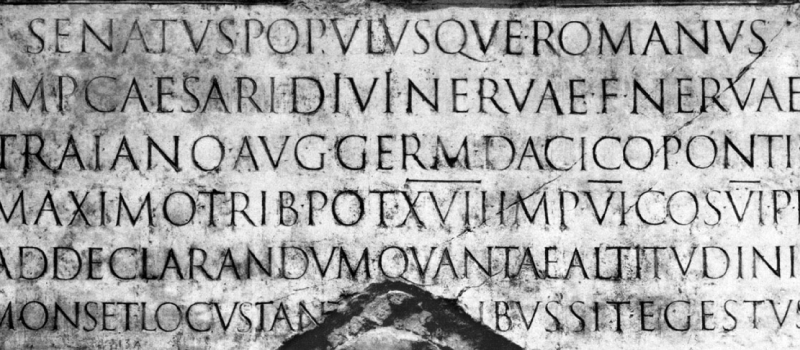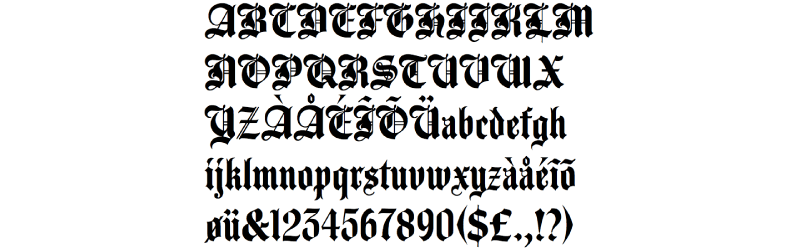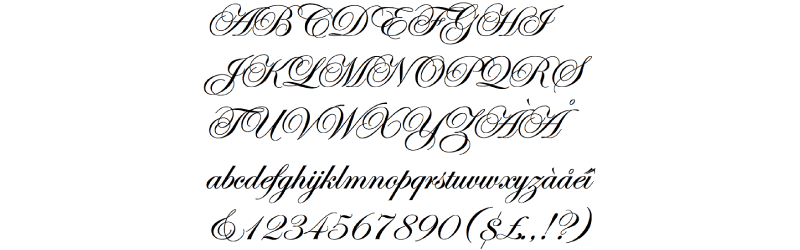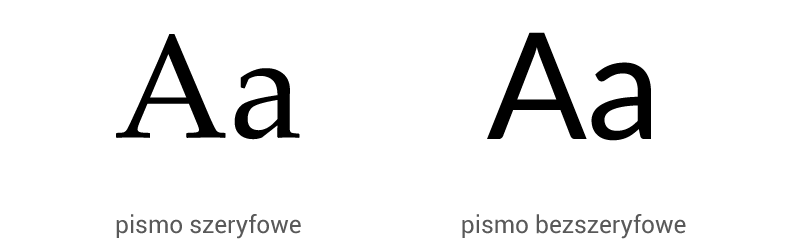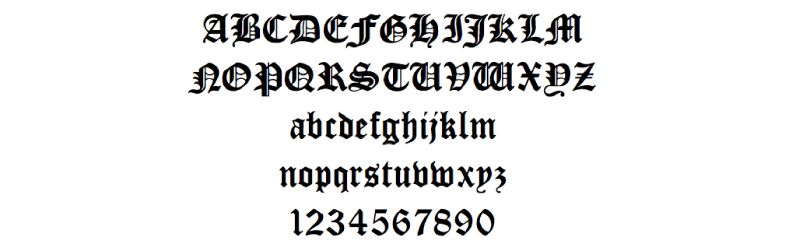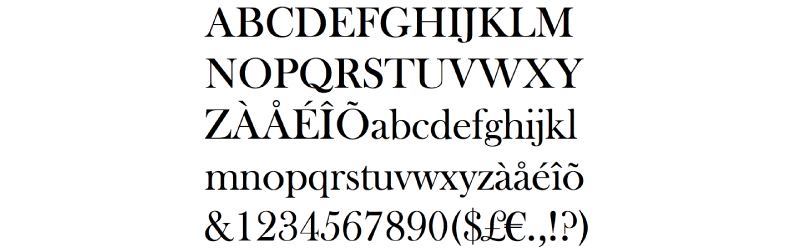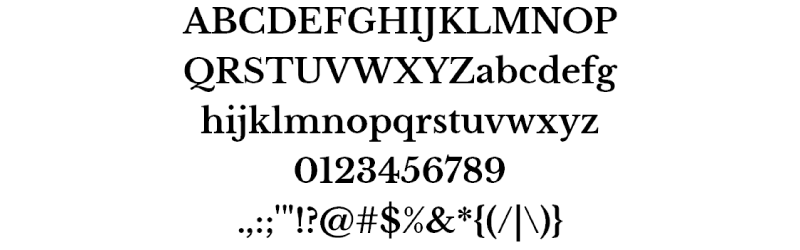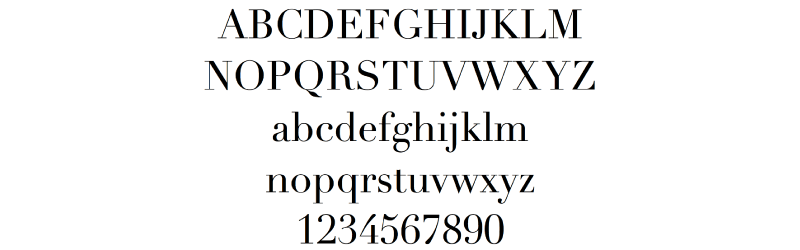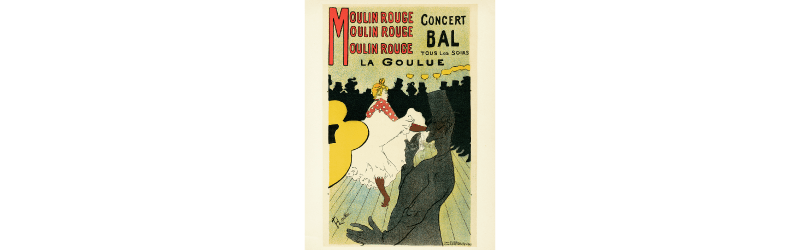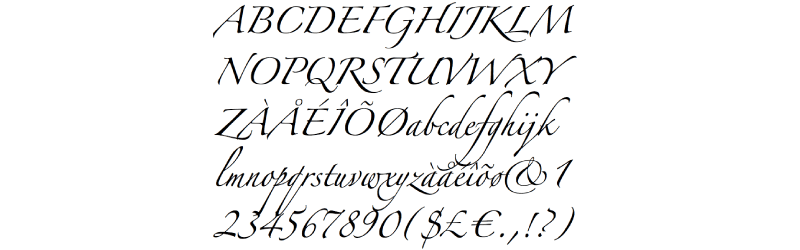
Z typografią stykamy się niemal wszędzie. Dobór kroju pisma może znacznie poprawić lub pogorszyć wygląd finalnego projektu, bądź podkreślić wartość merytoryczną przekazywanych słów. Coraz większą uwagę przykładamy do tego z jakiego kroju pisma korzystamy w różnych typach treści. Jednak skład tekstu nie sprowadza się tylko do wybrania odpowiedniego fontu - warto wiedzieć nieco więcej na ten temat, by tekst przez nas przygotowywany był łatwy do odczytania i zgadzał się z jego przeznaczeniem.
Skąd pochodzi nasz alfabet?
Na początek przyjrzyjmy się budowie liter. Alfabet rzymski, którym się posługujemy, wywodzi się ze starożytnego Rzymu, a pierwotnie służył wyłącznie do zapisu łaciny. Litery te mają charakterystyczne szerokie kreski na zakończeniu każdej linii tworzącej literę (szeryfy), a powstały one w wyniku technik, jakich wtedy używano - litery wykuwane były zapisywane za pomocą patyczka o ściętej pod skosem końcówce, lub wykuwane dłutem w kamieniu- oba narzędzia pozostawiały ślad w postaci takiej kreski właśnie. Rzymianie ogromną uwagę przykładali do harmonii optycznej w zapisie liter, stąd stosowanie węższych i szerszych linii w ich budowie, a także matematycznie obliczone wielkości zastosowanych liter. Dotychczas pismo zapisywane było wyłącznie za pomocą wielkich liter. Tablica z Kolumny Trajana na Forum Romanum jest uznawana za wzorzec litery alfabetu rzymskiego.
Podstawowe pojęcia z zakresu typografii to:
- majuskuła - wielka litera
- minuskuła - mała litera
- światło międzyliterowe - obszar niezadrukowany pomiędzy jednym, a drugim znakiem
- światło międzyliterowe - obszar niezadrukowany wewnątrz znaku
- kerning - odległość pomiędzy znakami
- ligartura - łączenia dwóch znaków
Podstawowymi rodzajami na jakie możemy podzielić kroje pisma są:
- pismo szeryfowe (serif) - czyli takie, w których występują szeryfy
- pismo bezszeryfowe (sans serif) - gdzie szeryfy nie występują
Nie istnieje jeden, ogólnie przyjęty system klasyfikacji poszczególnych krojów, jednak najbardziej popularnym jest system wprowadzony przez firmę Adobe i to na nim się skupimy.
Pismo gotyckie (Blackletter)
Ten typ krojów swą angielską nazwę zawdzięcza wrażeniu, jakie daje zadrukowana w ten sposób strona- wydaje się ona ciemna, a pismo ciężkie. Litery są zbudowane z linii o różnej szerokości.
Antykwy renesansowe (Old Face)
Ten typ to kroje lekkie, o zróżnicowanych szerokościach linii i subtelnych łukach.
Antykwy barokowe (Transitional)
Stanowią przejście pomiędzy antykwami renesansowymi a klasycystycznymi, dlatego zachowują niektóre cechy z obu typów. W odróżnieniu do antykw renesansowych posiadają większy kontrast w światłach znaków, a wydłużenia minuskuł zazwyczaj nie wystają ponad majuskuły.
Antykwy klasycystyczne (Modern, Didone)
Ten typ krojów pisma pojawił się wraz z techniką miedziorytu, który pozwalał na zastosowanie mocno kontrastowych grubości linii tworzących znak.
Antykwy linearne bezszeryfowe (Gothic, Sans Serif, Grotesque)
Wraz z rozkwitem przemysłu i reklamy zaczęto używać krojów bezszeryfowych, łatwiej czytelnych z odległości, świetnie nadających się na różnego rodzaju afisze i reklamy.
Pisanki
Wszystkie czcionki którymi obecnie się posługujemy mają swoje korzenie w którymś z powyższych typów. Istnieją jednak również tzw. pisanki - kroje, które imitują odręczny charakter pisma, w mniej lub bardziej ozdobny sposób. Z reguły dzielą się one na:
Pisanki kaligraficzne
pochodzące od kaligrafii, sprawiające wrażenie pisania wyprofilowanym pędzlem
Pisanki niedbałe
imitujące pismo wykonane zwykłym pisakiem bądź pędzlem
Pisanki gotyckie
powstałe w oparciu o średniowieczne manuskrypty, rzadko używane ze względu na utrudnioną czytelność
Pisanki angielskie
pochodzące od oficjalnego pisma odręcznego w XVIII w. Przez swoją elegancką formę często wykorzystywane w różnego rodzaju zaproszeniach, nagłówkach- wszędzie, gdzie zależy na wykwintnym oddziaływaniu znaków.
Obecnie najbardziej popularnymi krojami pisma są te bezszeryfowe, najczęściej inspirowane kształtami liter opracowanymi na potrzeby Helvetici. Doskonale sprawdzają się w zarówno w tekstach formalnych jak i tych nieoficjalnych. Warto jednak spróbować inne rozwiązanie, gdy pięknie napisany tekst zapada w pamięć i jego czytanie sprawia dużą przyjemność.